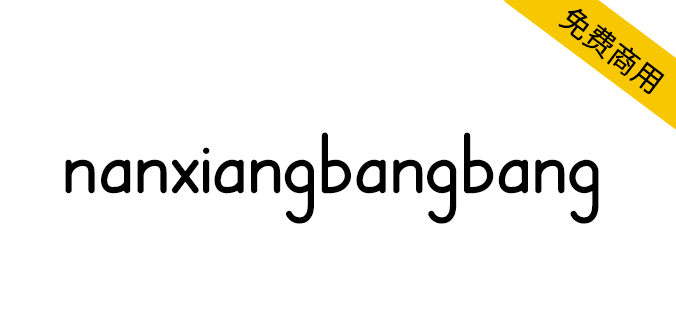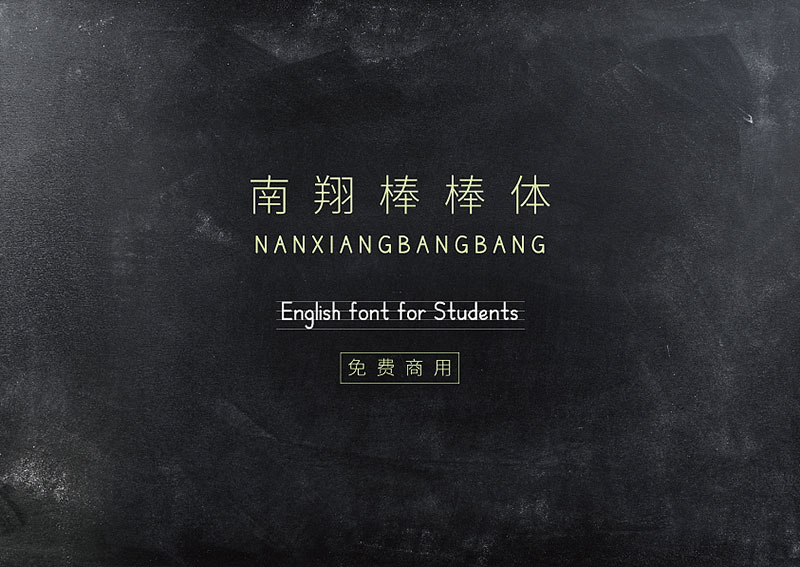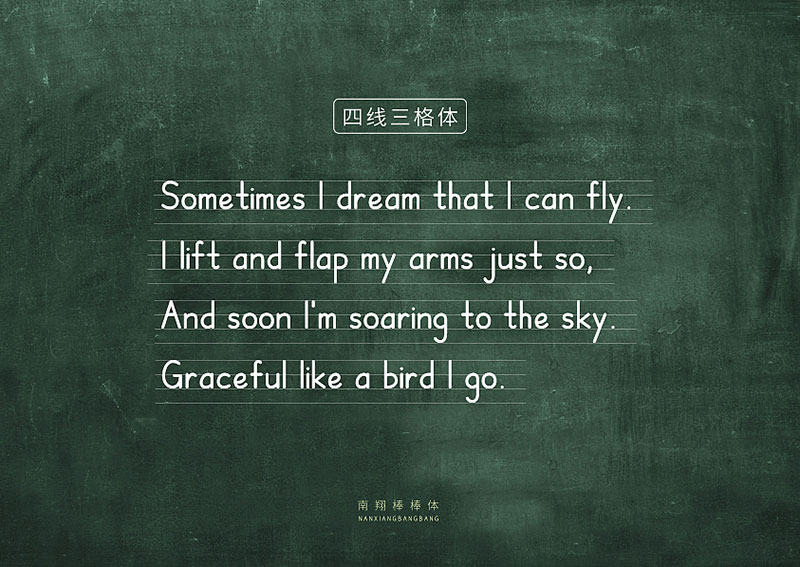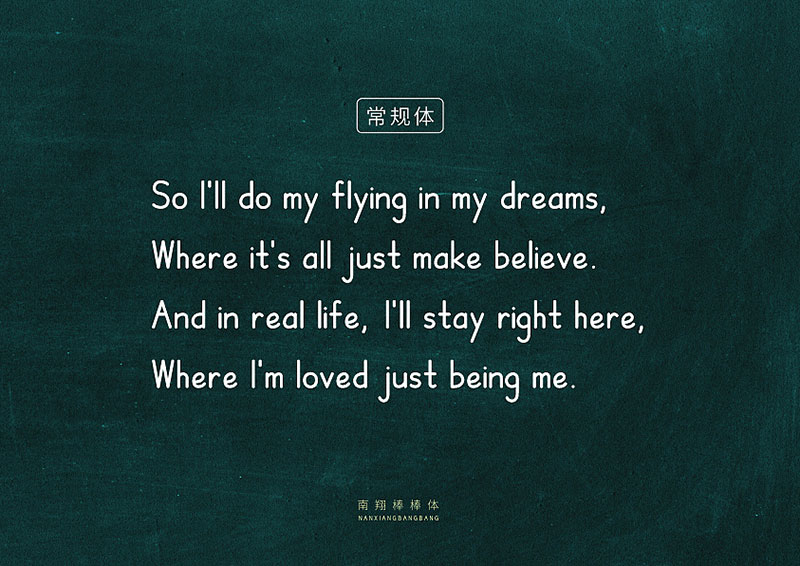
【nanxiangbangbang 南翔棒棒体】适用于棒棒体英文字帖
为了给儿子做个小学英文字帖,找了好久,上海要求学生书写的是一种叫做棒棒体的英文字体,和我们小时候的写法大相径庭,找了一圈也没有发现合适的字体!
索性自己做一套英文字体,包含:常规体、四线三格体、笔序体、笔序四线三格体,福利大众…
【nanxiangbangbang 南翔棒棒体】适用于棒棒体英文字帖